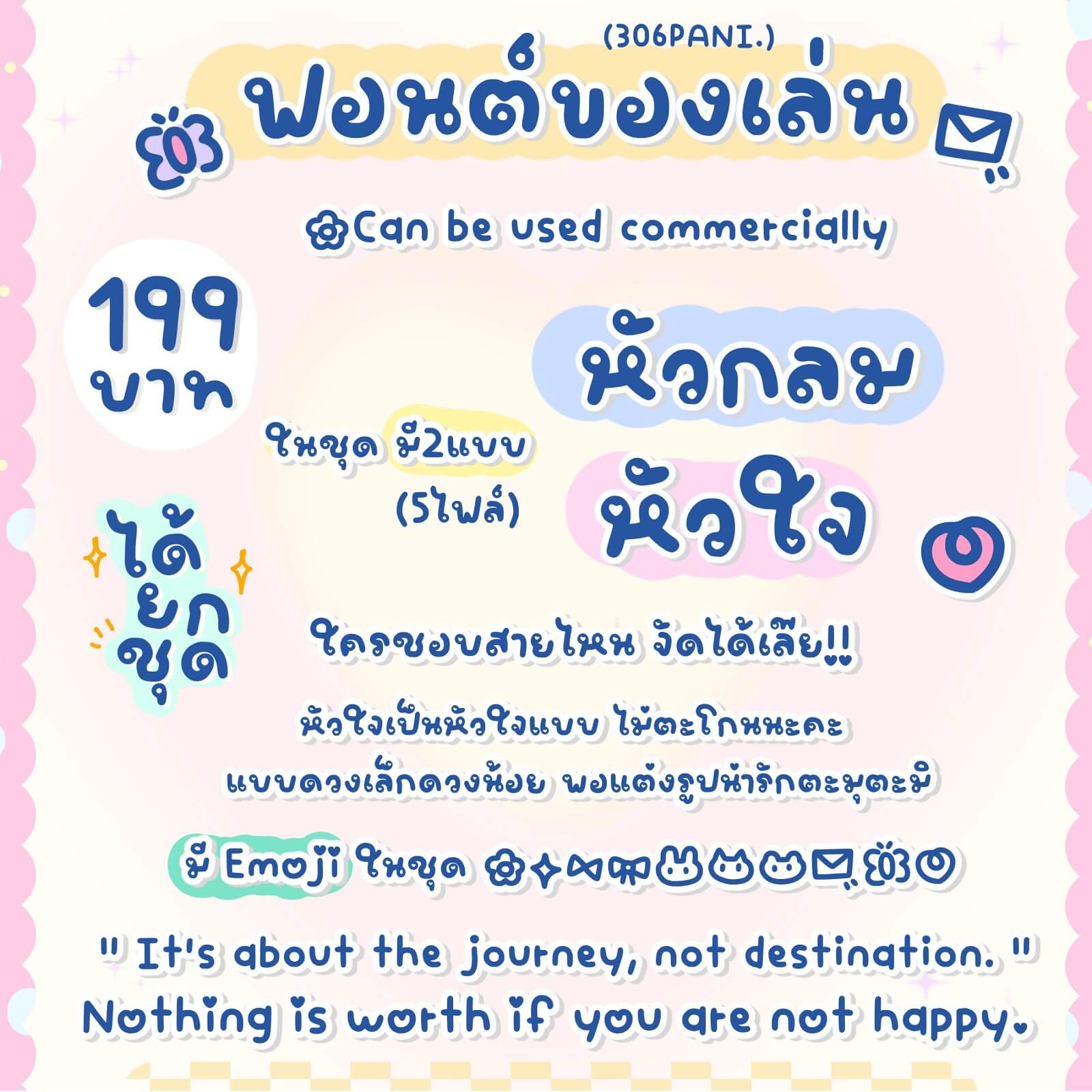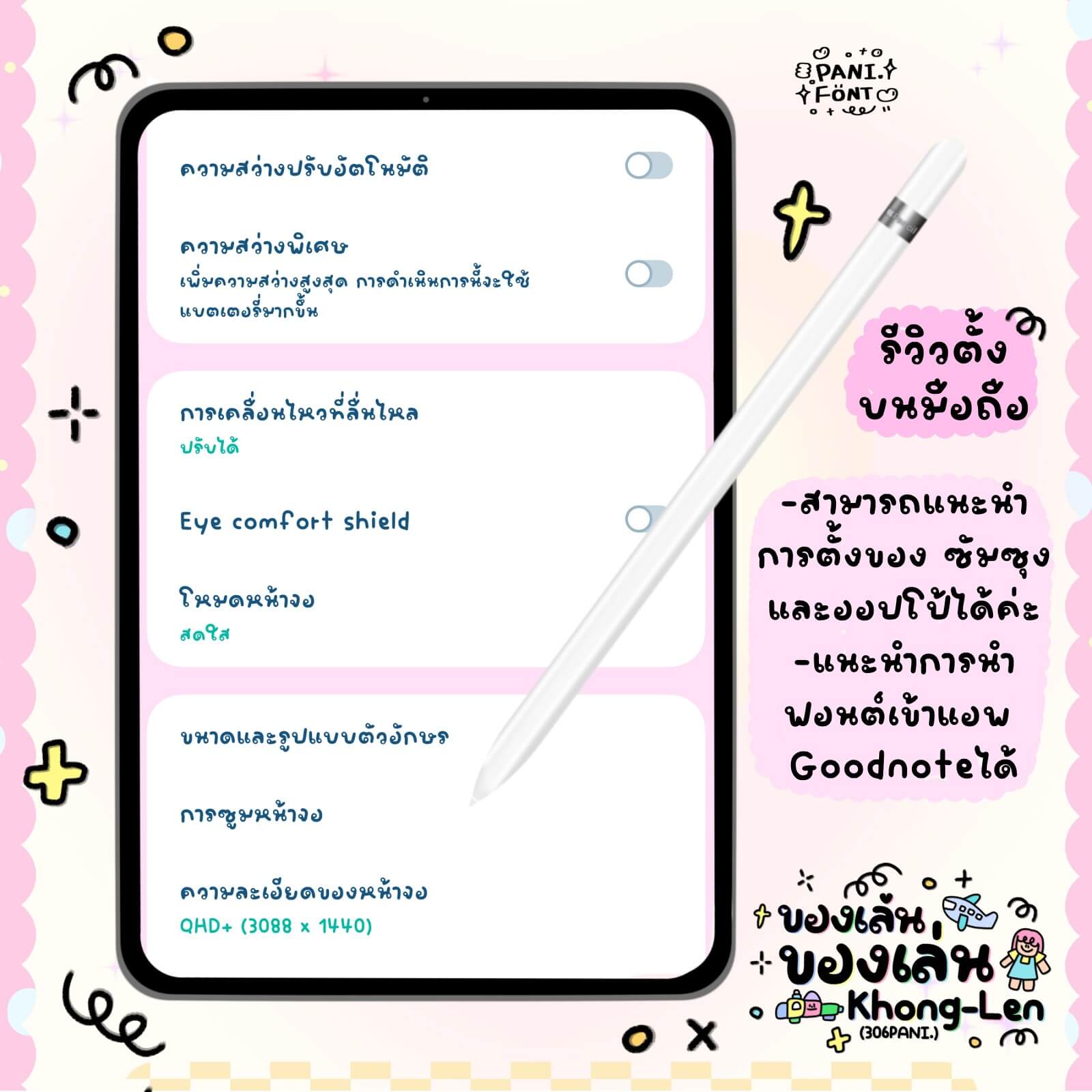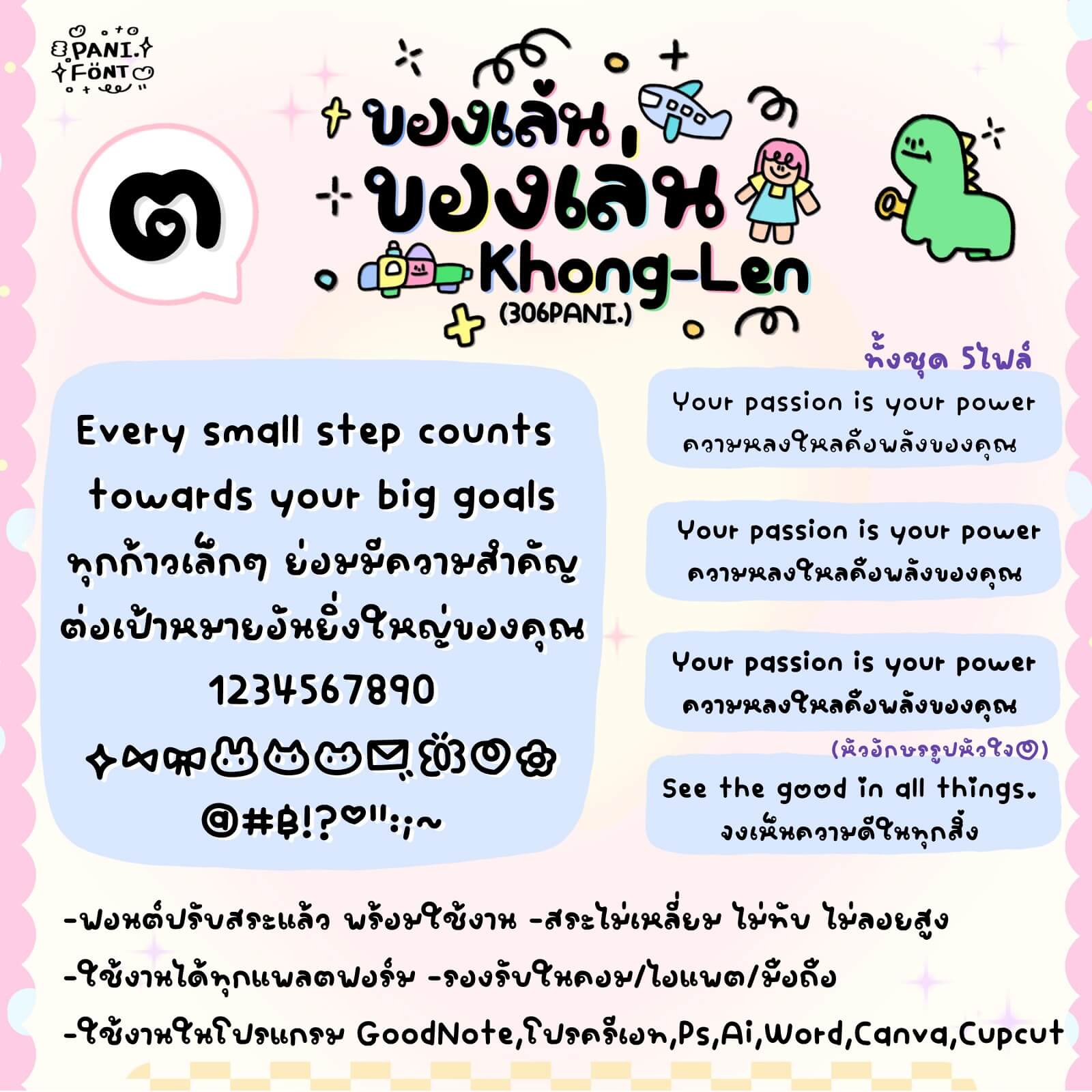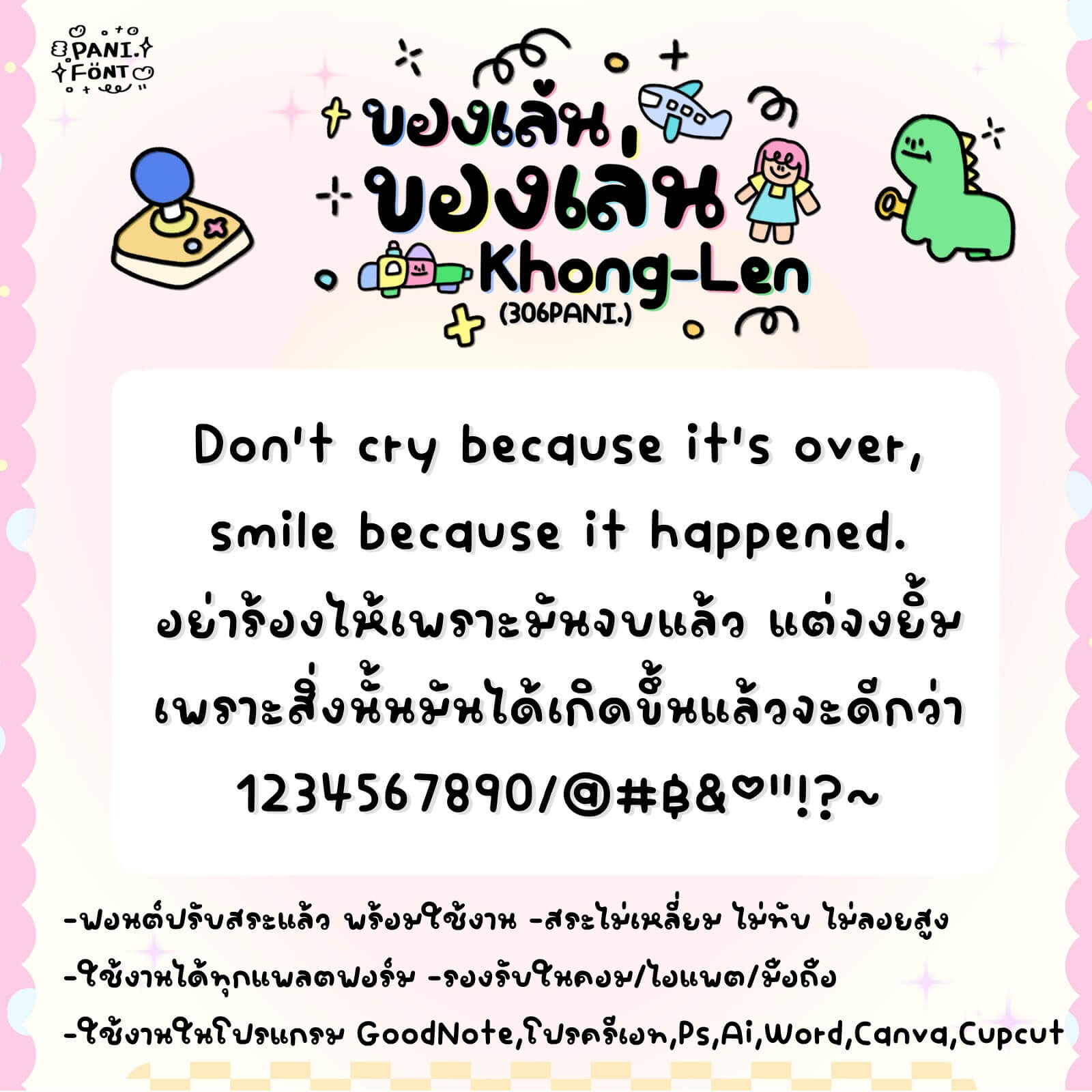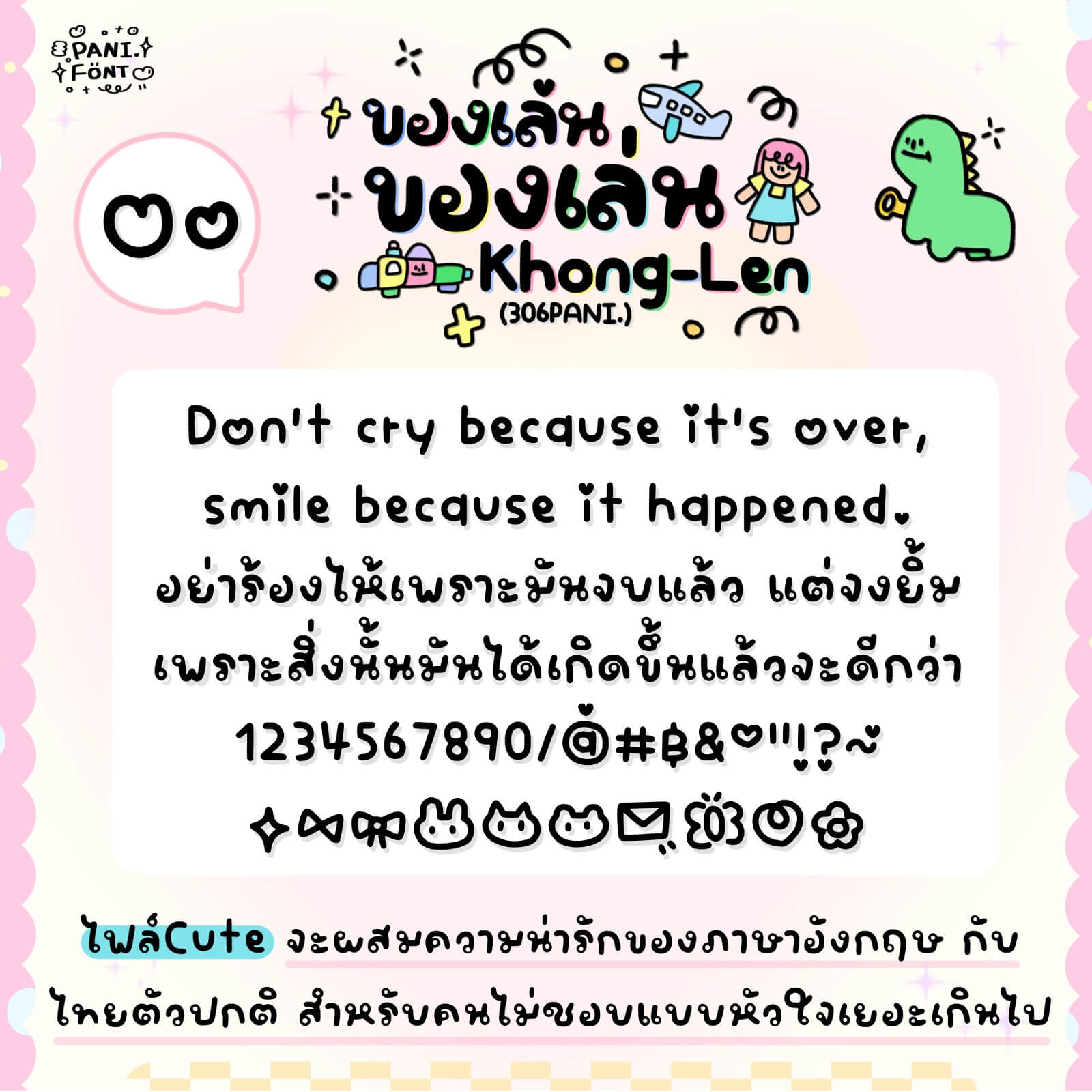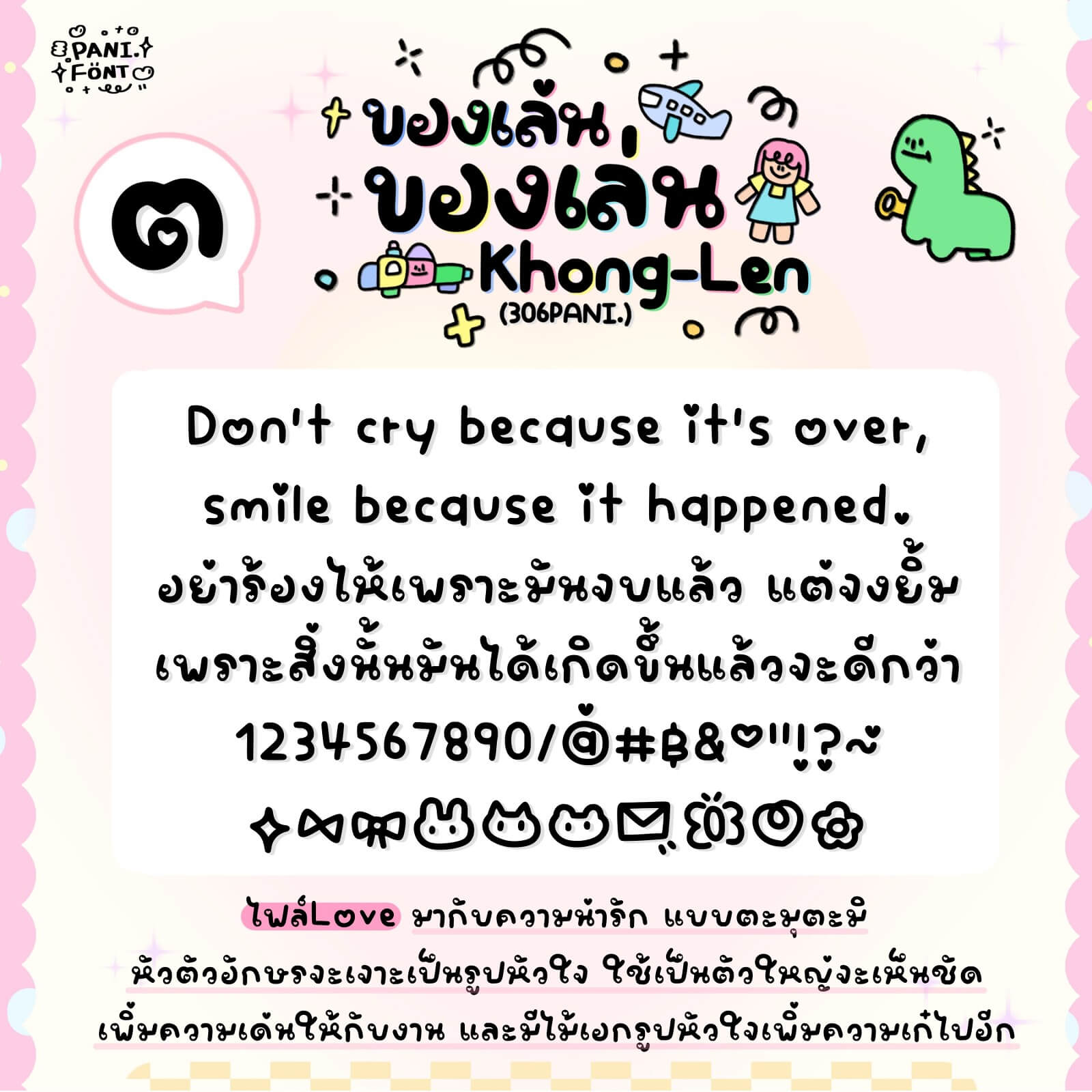
306PANI.ของเล่น
ฟอนต์ 306PANI.ของเล่น – ชุดนี้จัดเต็ม ฟอนต์เป็นตัวเข้ม เหมาะกับเป็นหัวข้อ หรือคนที่ชอบใช้ฟอนต์เข้มๆ นิดๆ ทุกอย่างดูตะมุตะมิ แบบไม่ตะโกน แอนแถมเพิ่ม ไฟล์ตกแต่งในชุดให้ด้วยค่ะ เผื่อไว้ใช้ตกแต่งภาพ สตอรี่ ได้หมดค่า
ฟอนต์มี 5 ไฟล์ – น้ำหนัก บาง ปกติ หนา Cute Love + แถมชุด ของตกแต่ง ไฟล์.png